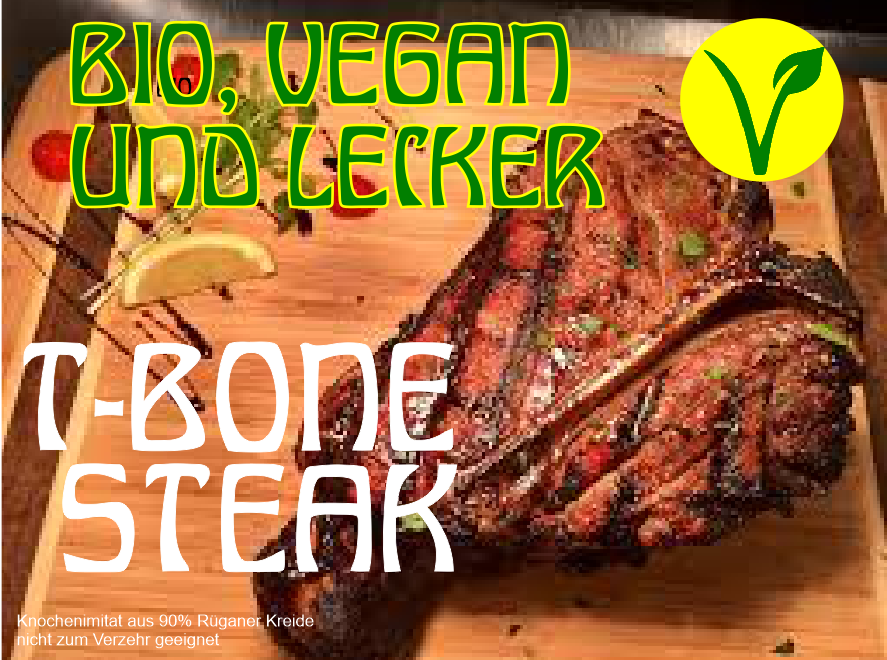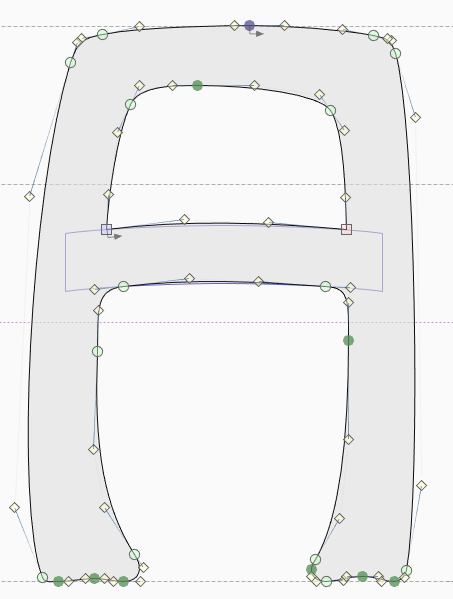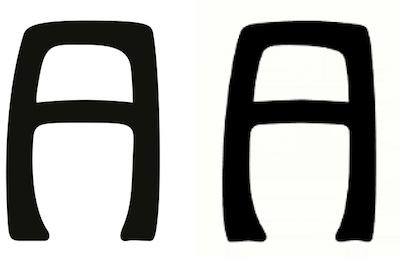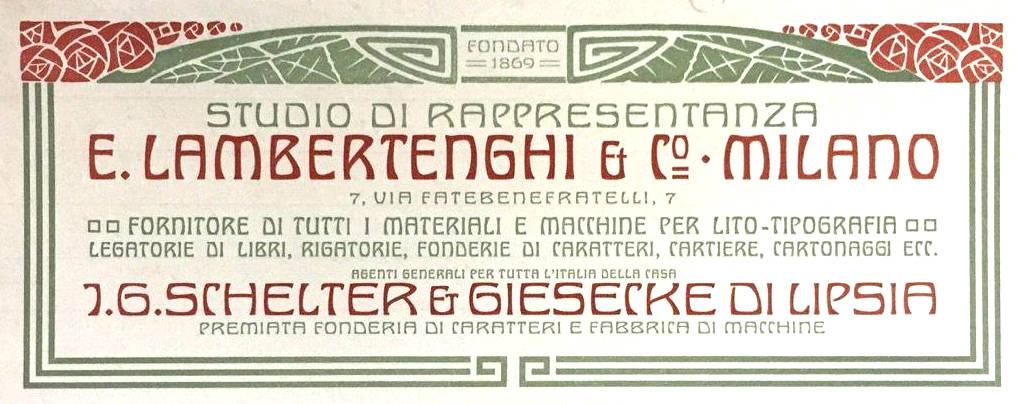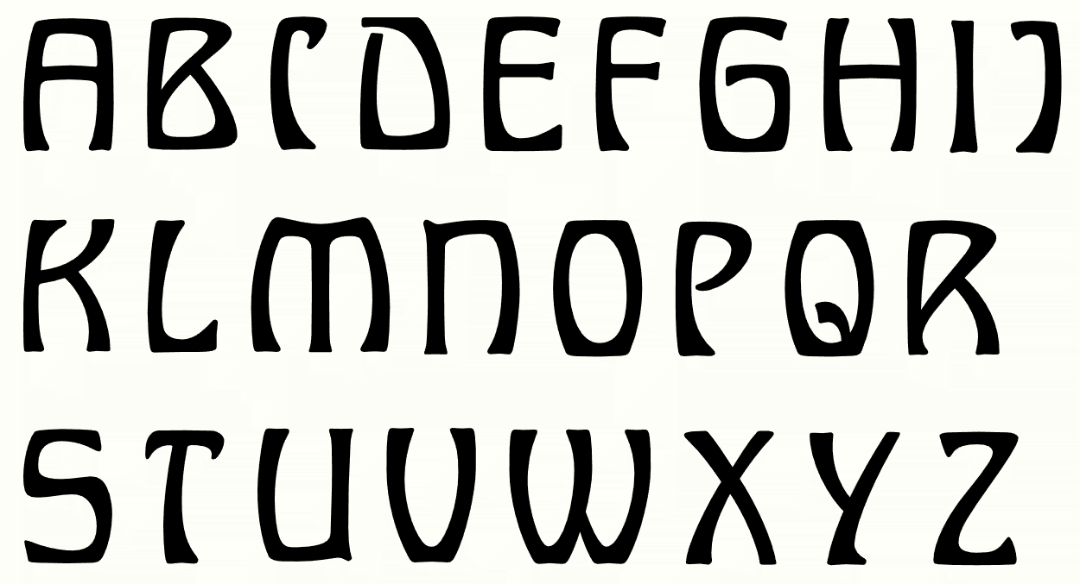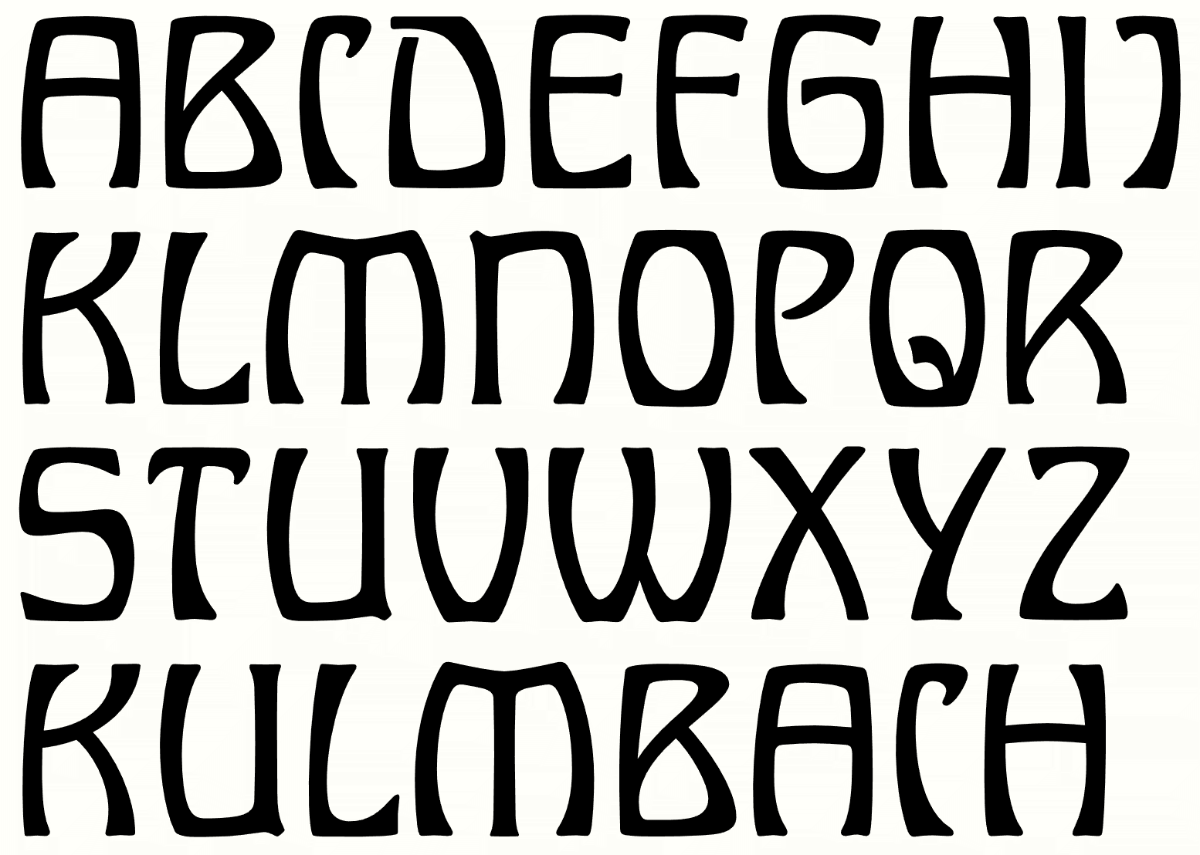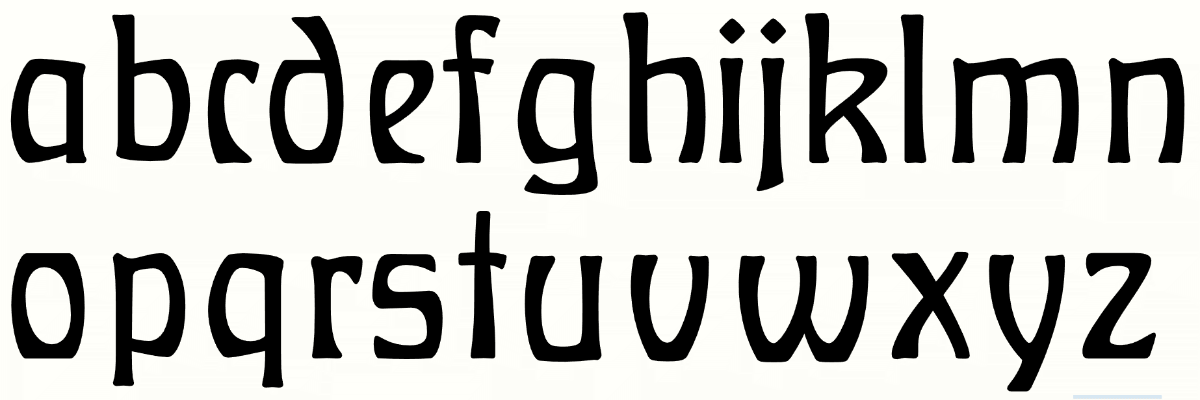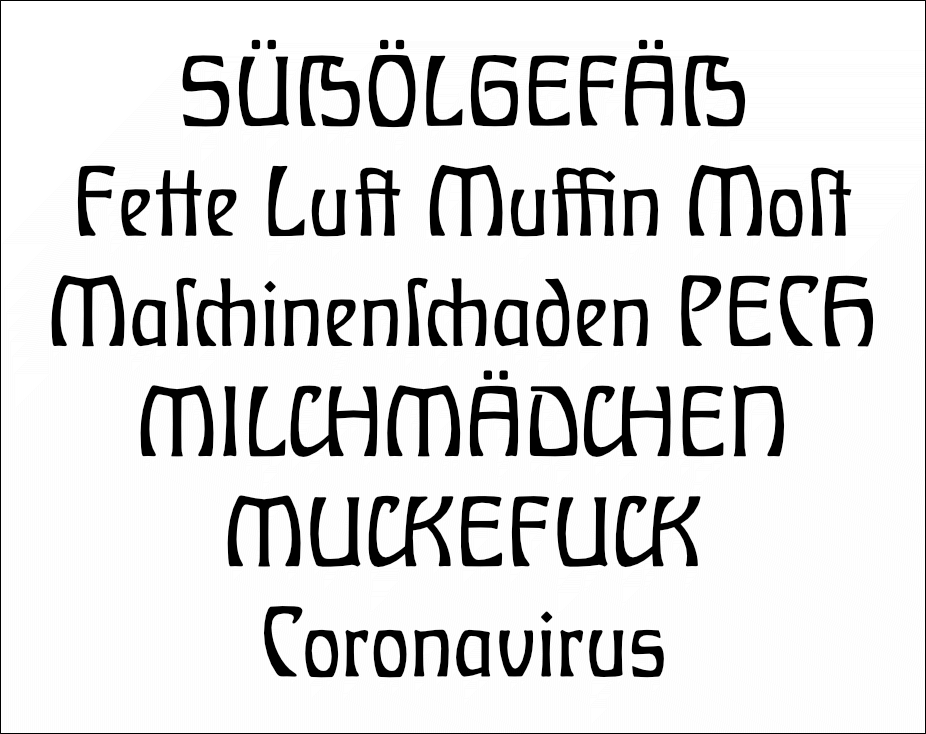
Jugendstil, die zehnte & elfte: Wittelsbach und Habsburg
Die Wittelsbach ist den vorhergegangenen Schriften verwandt. Aber weil sie nun mal so schön ist, und weil unser lieber Taurec mir eine komplette Probe zukommen ließ, ist sie am dransten.
Wie viele Schriften sollen das denn noch werden? Ich will ja nicht drängeln, aber freue mich nun doch schon soooooo lange auf das Erscheinen dieses Paketes ... dass die Freude schon fast wieder vergangen ist. Vielleicht wäre es ja denkbar zwei Pakete draus zu machen und die bisher fertigen schon mal zu veröffentlichen?
Gut Ding braucht Weile :-?
Besonders wenn man noch einen Hauptberuf und eine Familie hat. Bis frühestens Herbst wirst Du Dich gedulden müssen. Es werden zwölf Schriften, plus ein Satz Ornamente, Bordüren und Vignetten.
Hier sind die Großbuchstaben mal grob gezeichnet. Da ist noch nichts angepaßt oder ausgeglichen. Da diese Schrift etwas ausgesprochen Handgeschriebenes hat, habe ich größtenteils auf die Verwendung von Bausteinen verzichtet, und jeden Buchstaben komplett gezeichnet. Etwas gleichmäßiger dürfen die Strichstärken aber noch werden. Auch die Rundungen sollten kantiger sein.
Na ja, so fernab ist die ja tatsächlich nicht, kommt sie ja aus der Zeit, in der das aufkahm, und si sehe ich generell eine Schrift aus solchem Dunstkreis - was ja durchaus auch einen Ansatz für aktuelle Nutzung eröffnet:
Dem C könnte man eventuell noch eine etwas klassischere/breitere Alternative zur Seite stellen ...
Das schmale C tritt bei einigen dieser Schriften auf. Ich vermute, C war für die Kombinationen CH und CK ausgelegt und sollte selbst wenig Raum einnehmen. Ein Buchstabe zweiter Klasse, sozusagen.
Sieht doch schon gut aus – ich würde aber noch ein bisschen klarere Linien ziehen, da sie sonst ein bisschen zu anthroposophisch aussehen könnte, oder?
Norbert, was meinst Du mit "klaren Linien"? Hättest Du ein Beispiel?
Hier mal ein Einwurf: Aus der fertigen Wittelsbach könnte ich gut die Habsburg ableiten, die größtenteils eine breitere, lichtere Version der Wittelsbach ist. (Gott, hier fing es gerade an aus heiterem Himmel zu donnern an, daß die Fenster wackeln) Jetzt überlege ich mir, wie ich das in Fontlab am einfachsten ohne Mehrarbeit mache. Horizontal skalieren geht ja nicht, denn dann werden auch die stems (Deutsch?) breiter.  Ich habe mal das TypeRig mit DeltaMachine runtergeladen. Das ist mir aber noch ein Buch mit sieben Siegeln. Vielleicht hat jemand da eine Idee...
EDIT: die Power Guides in Fontlab machen das anscheinend. Ich probier's mal.
Eventuell weniger Ankerpunkte? Bzw. nur das Mindestmaß an Punkten?
Ah, ok. Weniger Punkte wird schlecht gehen, ich bin aber noch nicht mit dem Polieren fertig. Auch mache ich die Screenshots ziemlich klein.
Startschwierigkeiten mit den Powerguides sind bewältigt! Jetzt wird's also auch die Habsburg geben. Die scheint mir übrigens noch anthroposophischer auszusehen – fast schon homöopatisch!
Hier die Kleinbuchstaben im ersten Durchgang grob gezeichnet. Das ging fix, aber jetzt heißt es "langsam mit de Kiah, sonscht wackelt 's Oiter ônd nô kriagat mr Bolle in'd Milch". Bis das alles schön gleichmäßig zusammen paßt, verschwinde ich mal in der Versenkung.
In Zeiten von Corona sollte man das vielleicht überdenken ... :-P
ch und ck Ligaturen sind im Original vorhanden. Vielleicht mache ich das auch für die Großen. Im Moment kämpfe ich noch mit den Gemeinen.
Es wird...
Die Schrift ist jetzt soweit fertig, nur die eine oder andere Ungereimtheit ist noch auszumerzen. Weiteres also in Kürze 🙂
Das obige war nur ein Zuckerl für mein Instagram. Eine vollständige Probe steht noch aus. Hier aber einige der von mir dazu gedichteten Formen. Nochmals vielen Dank an @catfonts und @Microboy für die Anregung zum breiten C und CH und CK.